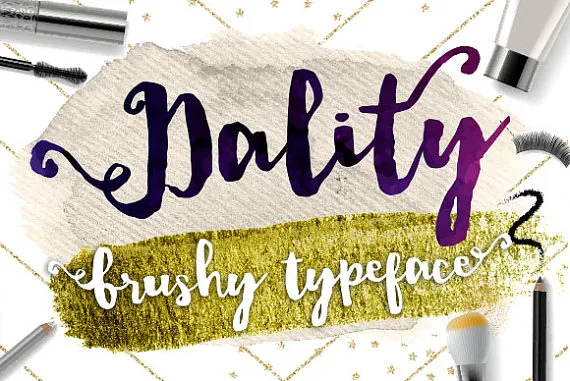
Dality Font – Download Grátis
A Dality Font é uma seleção única para aqueles que buscam um estilo moderno e brushy, perfeito para adicionar um toque vibrante a qualquer projeto. Desenvolvida pelo designer Hamilton, essa fonte script incorpora elementos de linhas eretas e traços fluidos em sua composição, criando um contraste interessante e dinâmico que combina elegância com agressividade. Perfeita para anúncios digitais e design gráfico moderno, a Dality Font oferece uma forma versátil para incorporar cores vibrantes e texturas modernas em qualquer projeto. Seja em logotipos ou materiais de marketing digital, essa fonte traz ao seu trabalho um ar contemporâneo que destacará sua criação com originalidade. Não importa o formato do seu projeto, a Dality Font é uma opção inteligente para designers buscando incorporar novas ideias sem comprometer a estética tradicional ou sofisticada de seus designs.